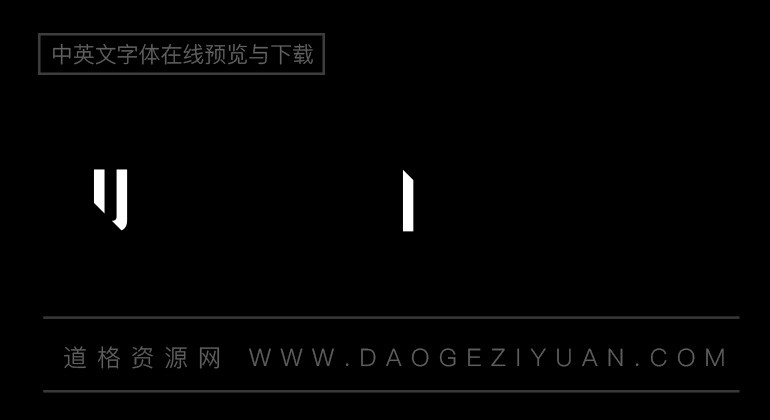
Universal Ignorance
Universal Ignorance 是一款由英国设计师Rob Clarke设计的手写字体,它拥有独特的手写风格,具有灵活的外观,每个字母都有自己独特的特点,它可以在多种不同的文字类型中使用,包括标题、标签、标语和标题。它的特点是易于阅读,易于理解,而且具有丰富的文字细节。Universal Ignorance字体可以用于各种类型的设计,可以添加更多的个性和艺术感,适合用于商业、品牌和个人设计。
Universal Ignorance是一款非常不错的手写艺术字体,具有很好的视觉感,适合于文化类的宣传设计、商业类品牌的广告和产品包装设计以及个性化文字排版等较多场景。